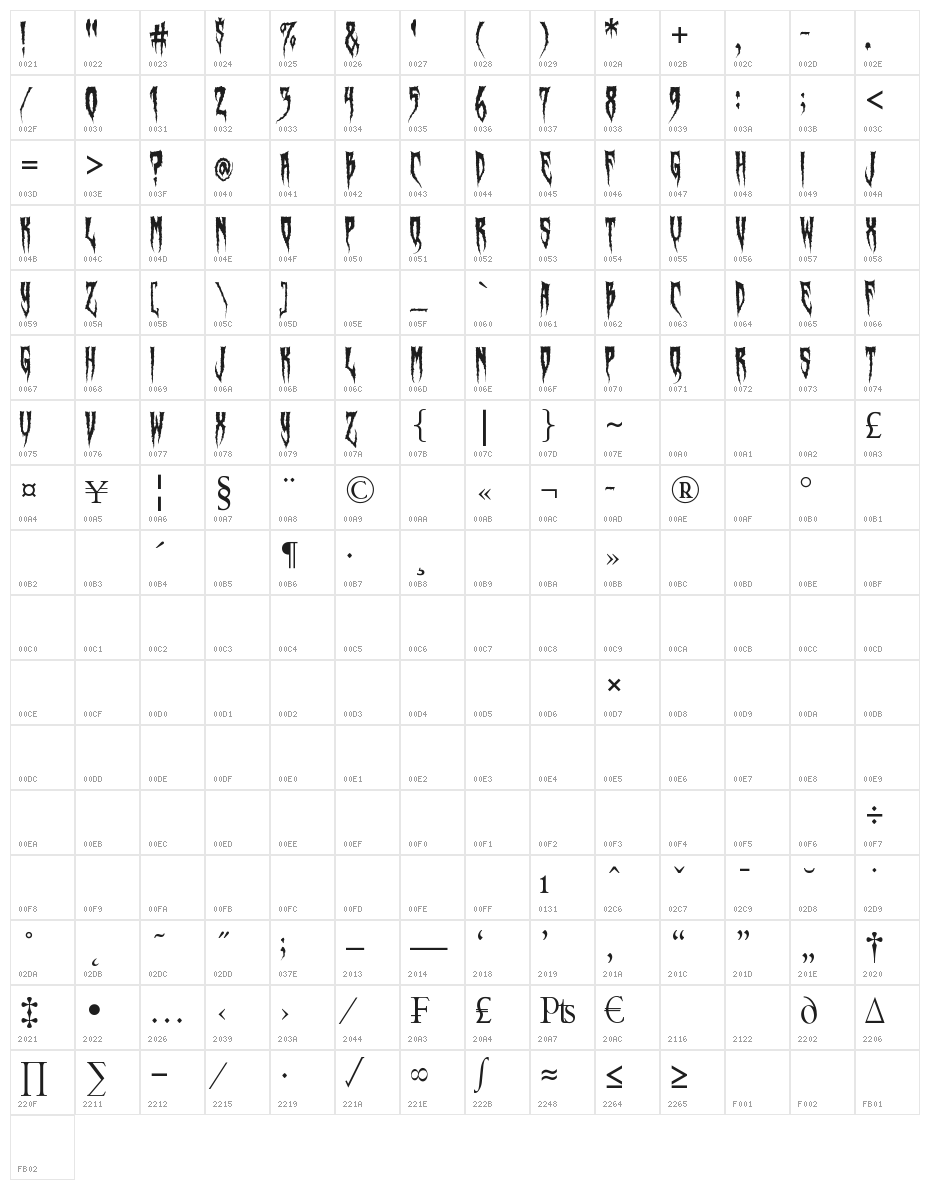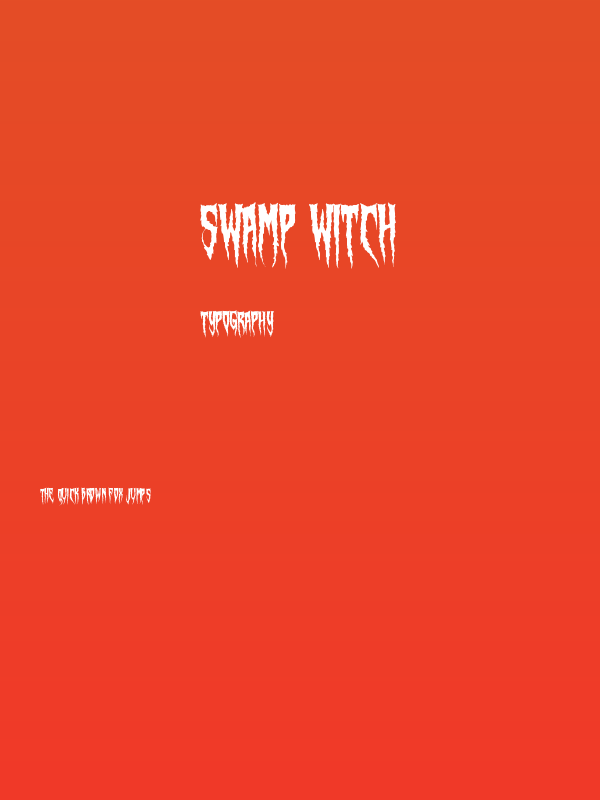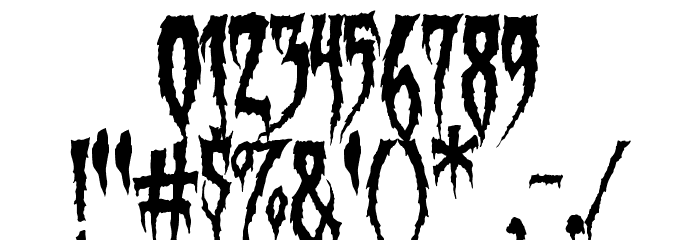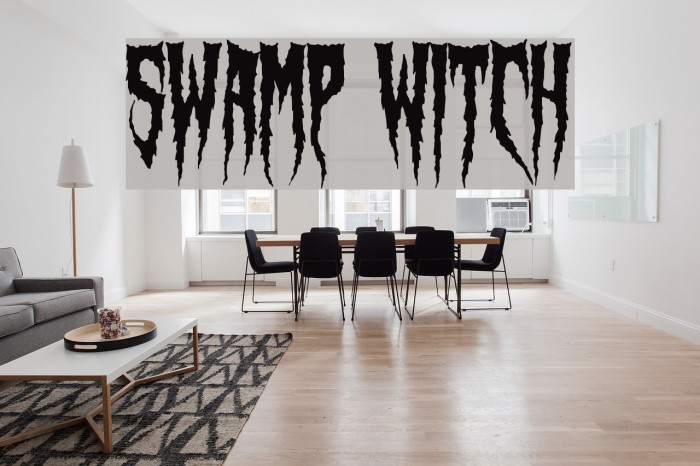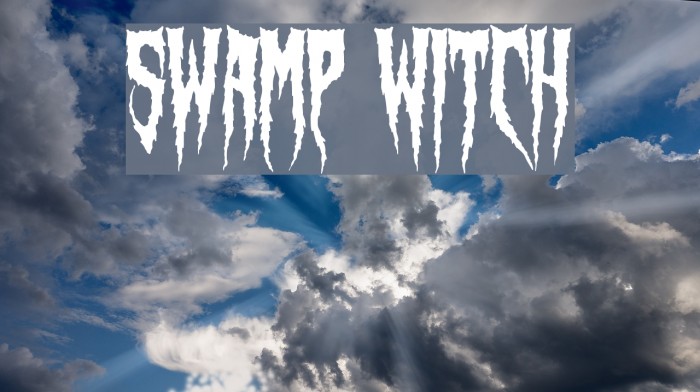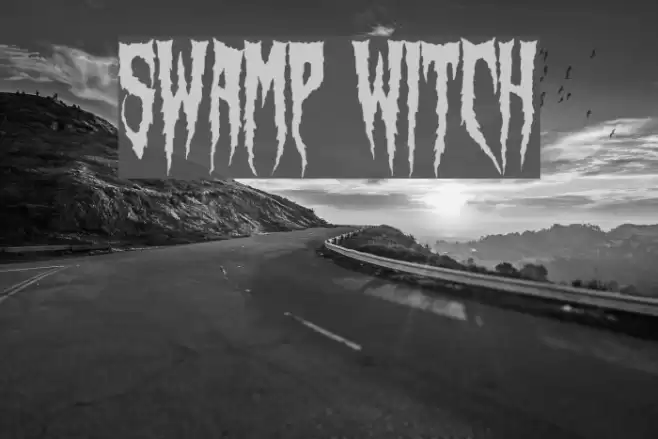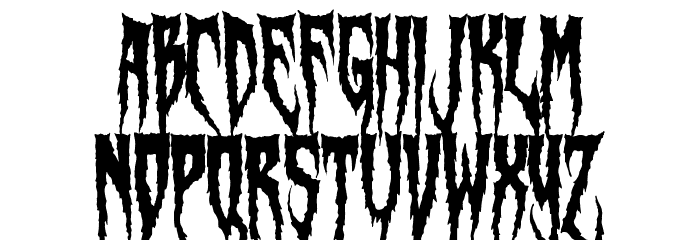
Swamp Witch Font
| Proiecte propuse | Perfect for Halloween-themed designs, horror movie posters, haunted house flyers, and gothic event invitations. |